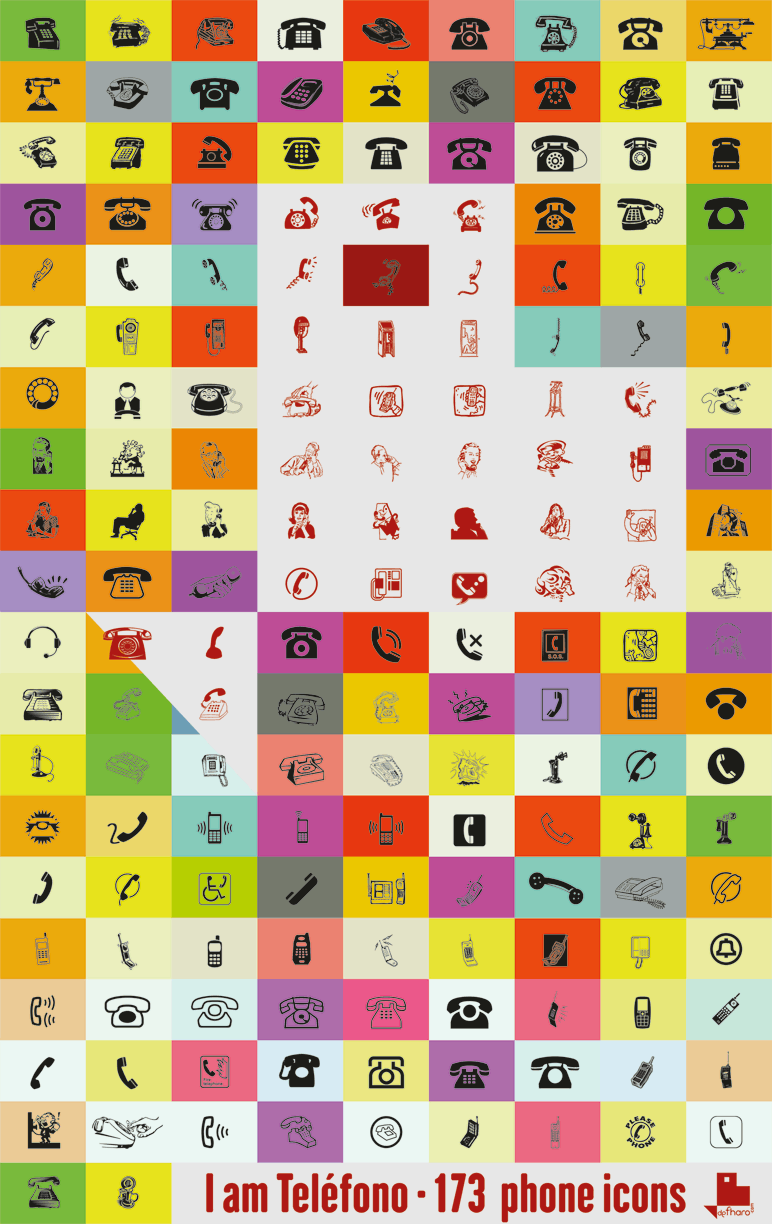
Cualquier diseñador gráfico sabe que tener a mano ciertos iconos o clips art de uso común y para trabajos de todo tipo, es algo que, le evitará a última hora, buscarse la vida encontrando el símbolo adecuado o bien dibujarlo.
En esta ocasión he compilado en una dingbats font (I am teléfono), mi colección particular de símbolos de teléfono que durante años reuní en un archivo Freehand, todos son iconos relacionados con telefonía, los iba encontrando y también de vez en cuando dibujaba alguno para tal o cual trabajo, finalmente he recopilado los mejores: 173 iconos de teléfonos, y los he convertido a línea de arte con la exigencia que para el diseño de vectores tiene el editor de tipografía Fontlab. Encontraréis en esta serie, vectores limpios y optimizados que sirven para cualquier uso profesional, incluido el corte de vinilo.
Por fin, los he ordenado por formas, estilos y tipos, encontraréis en esta fantástica colección de signos, iconos y símbolos: teléfonos retro y vintage, teléfonos divertidos, formales, geométricos, en movimiento… también ilustraciones de personas y personajes con teléfonos en la mano, espero que encuentres el estilo gráfico adecuado para cada ocasión creativa.